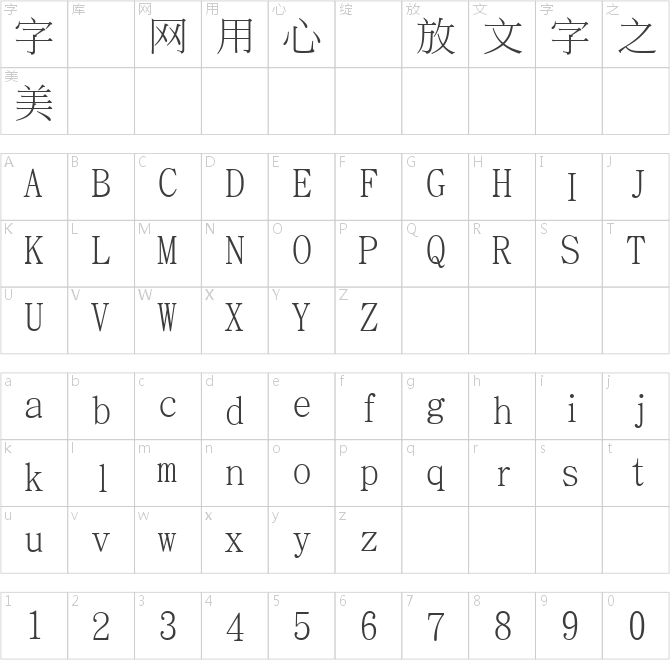
臺灣教育部標(biāo)準(zhǔn)宋體 詳情頁
宋體
臺灣教育部標(biāo)準(zhǔn)宋體字體字庫是一款讓人賞心悅目、百看不厭的中文字體,適合各類廣告和產(chǎn)品包裝設(shè)計(jì)應(yīng)用,字體大小20.28MB,格式為ttf字體,上傳用戶是123123aaa,作者/版權(quán)方為未知